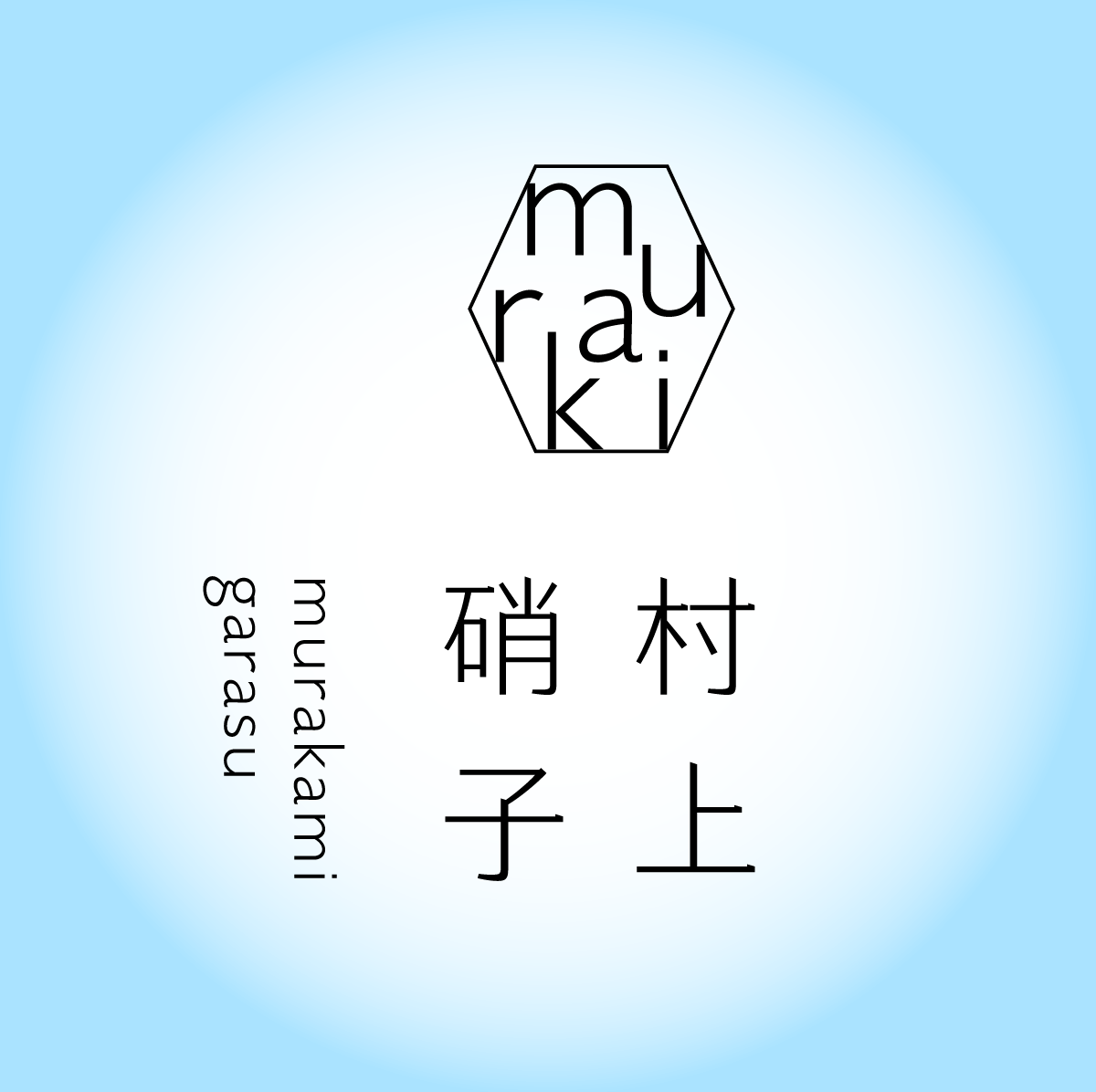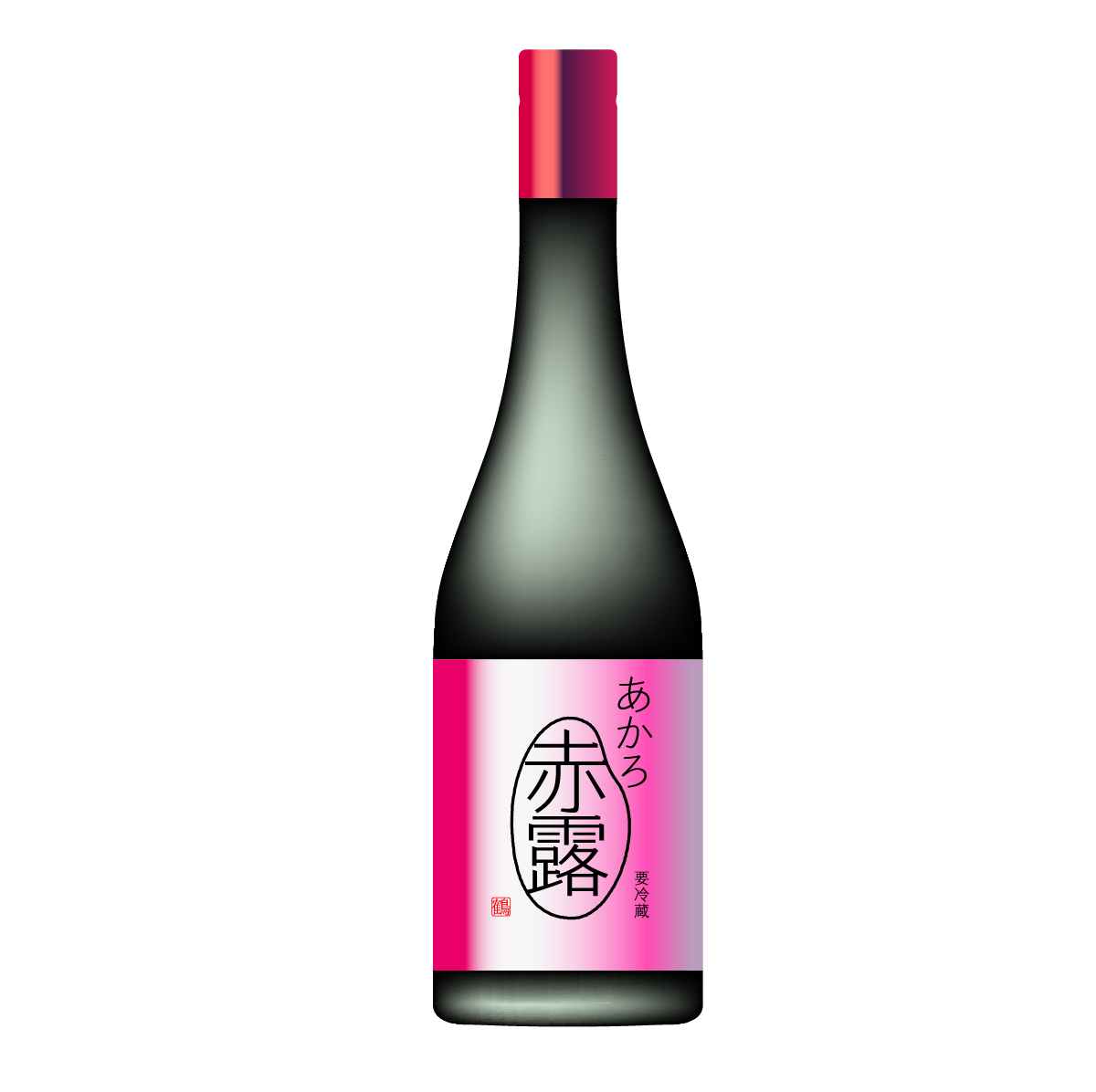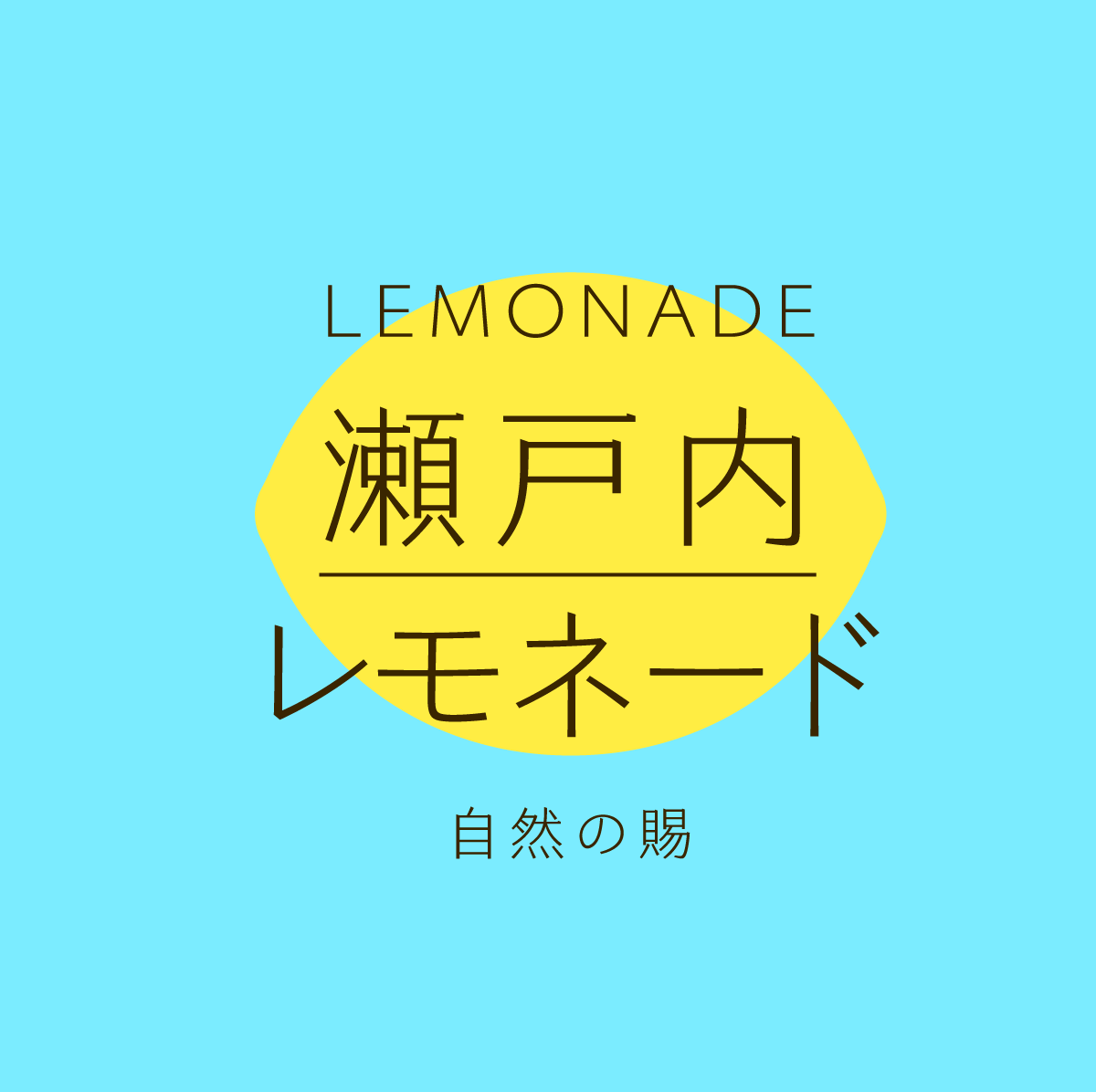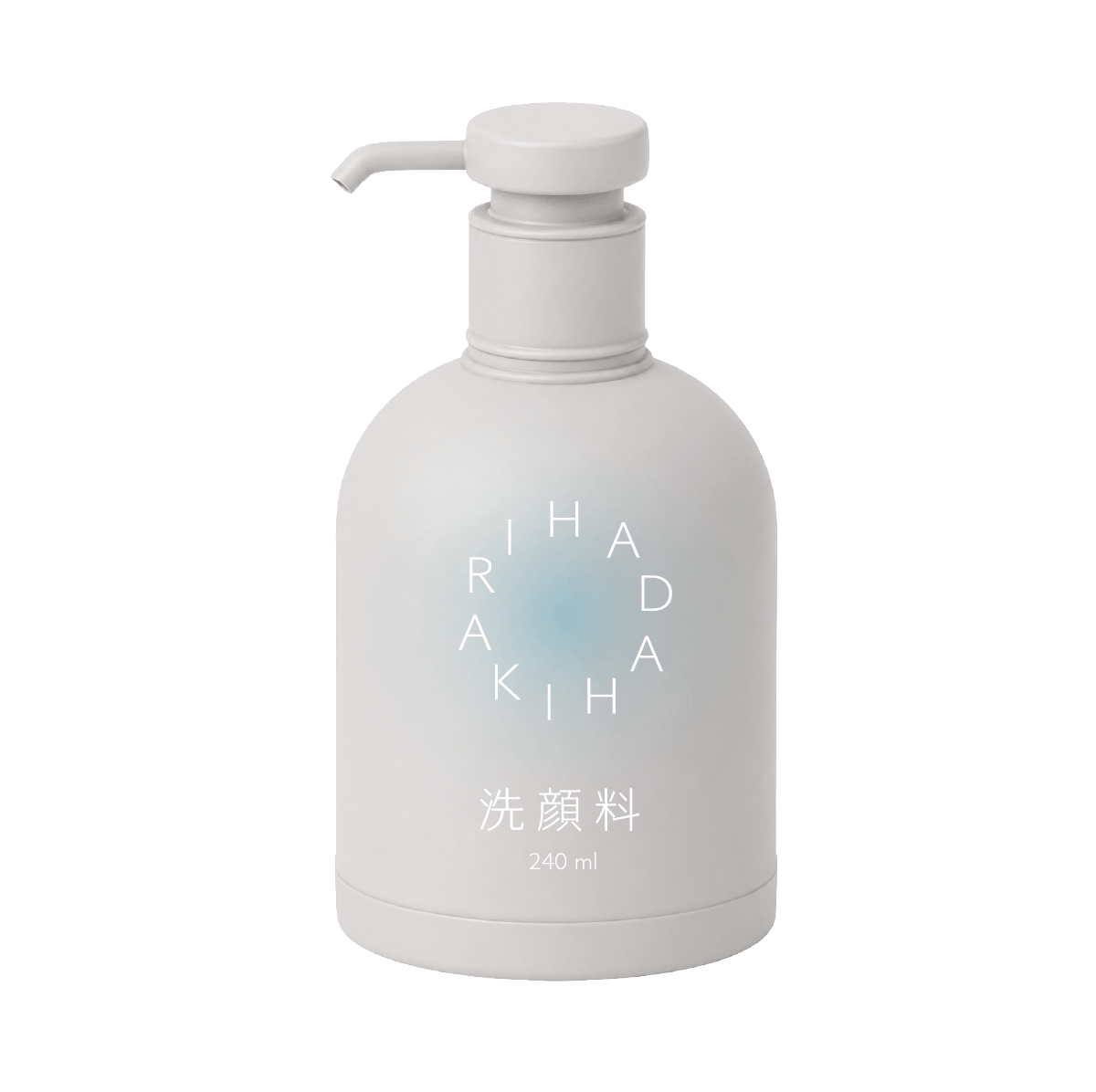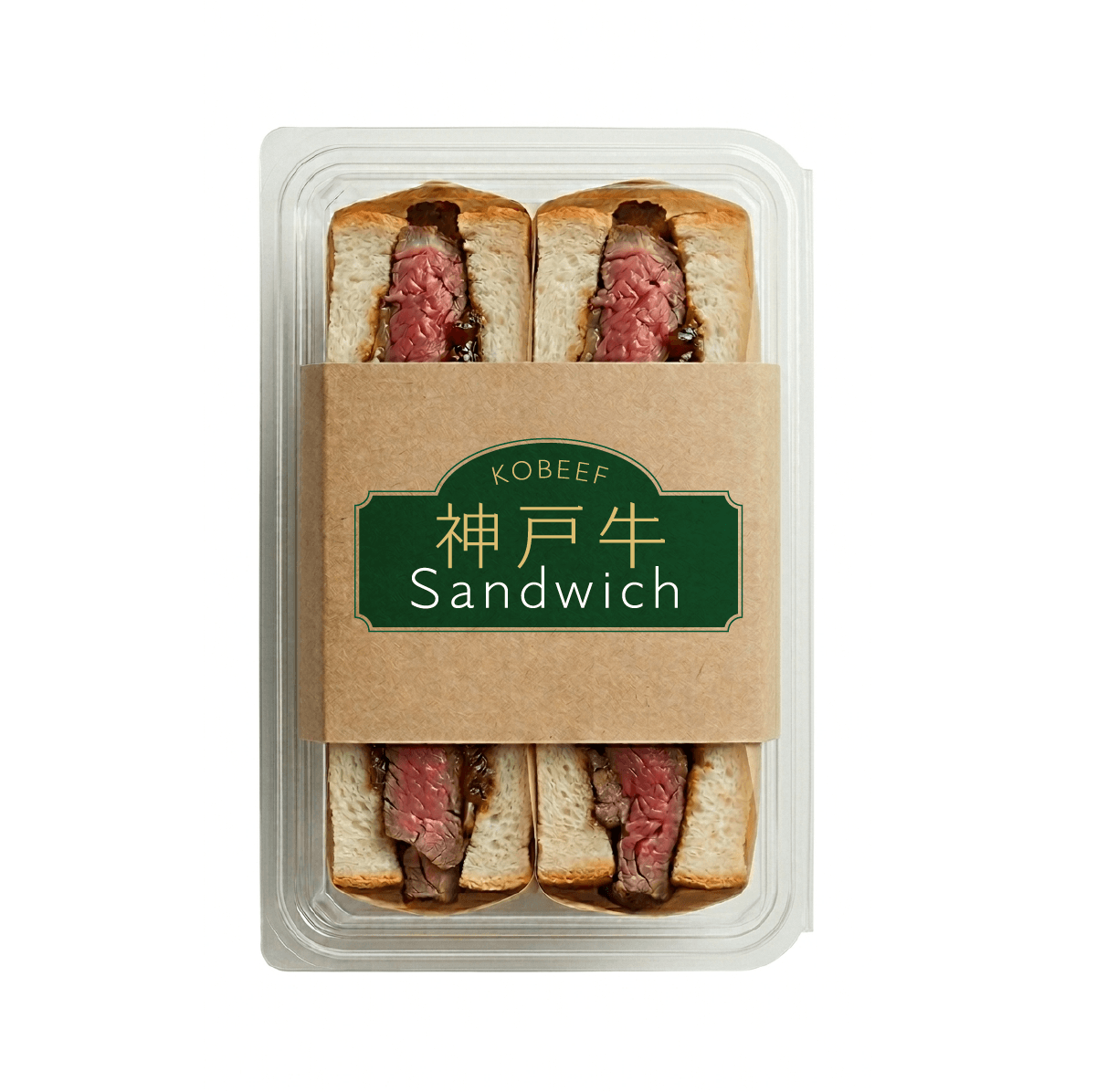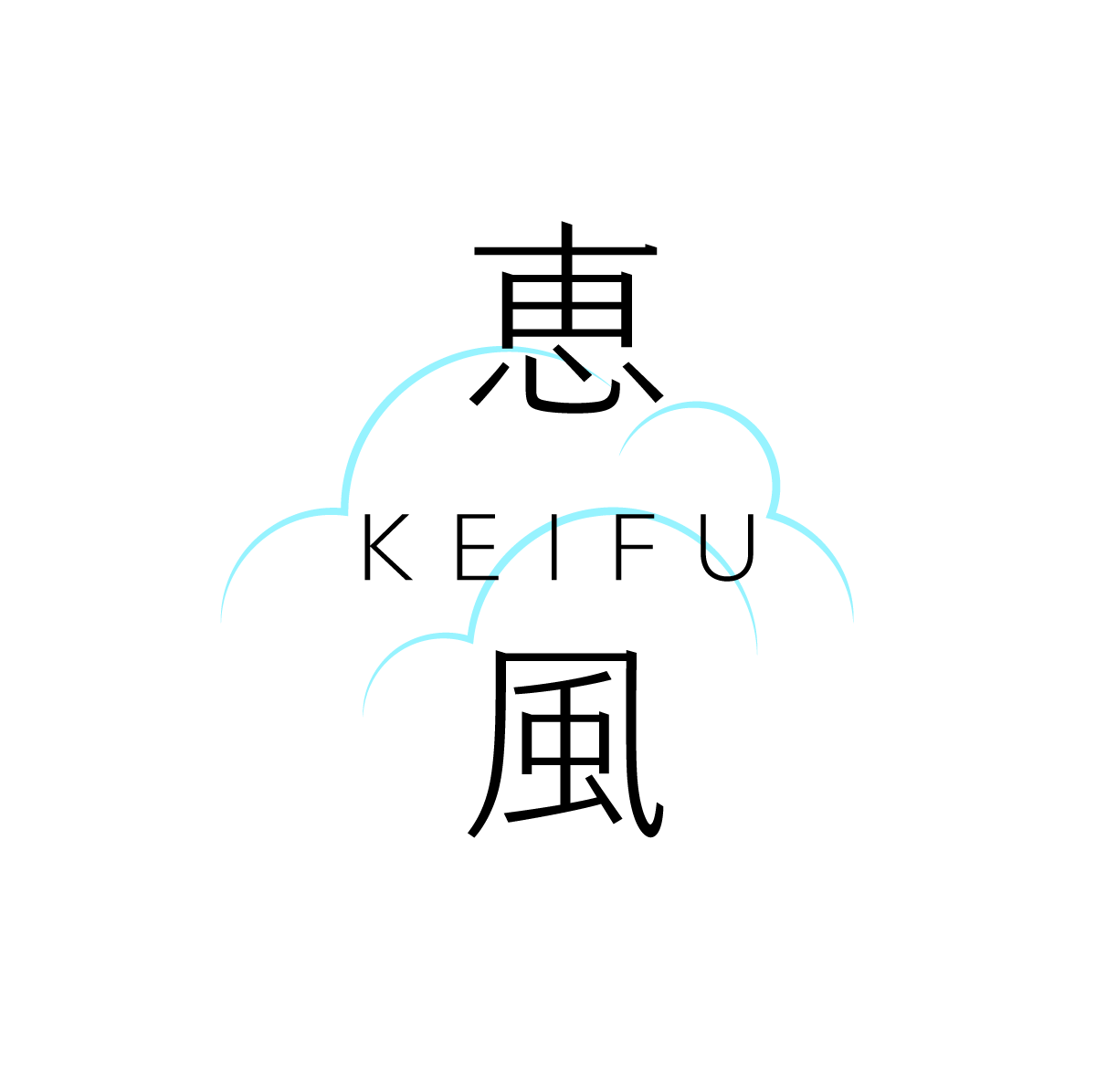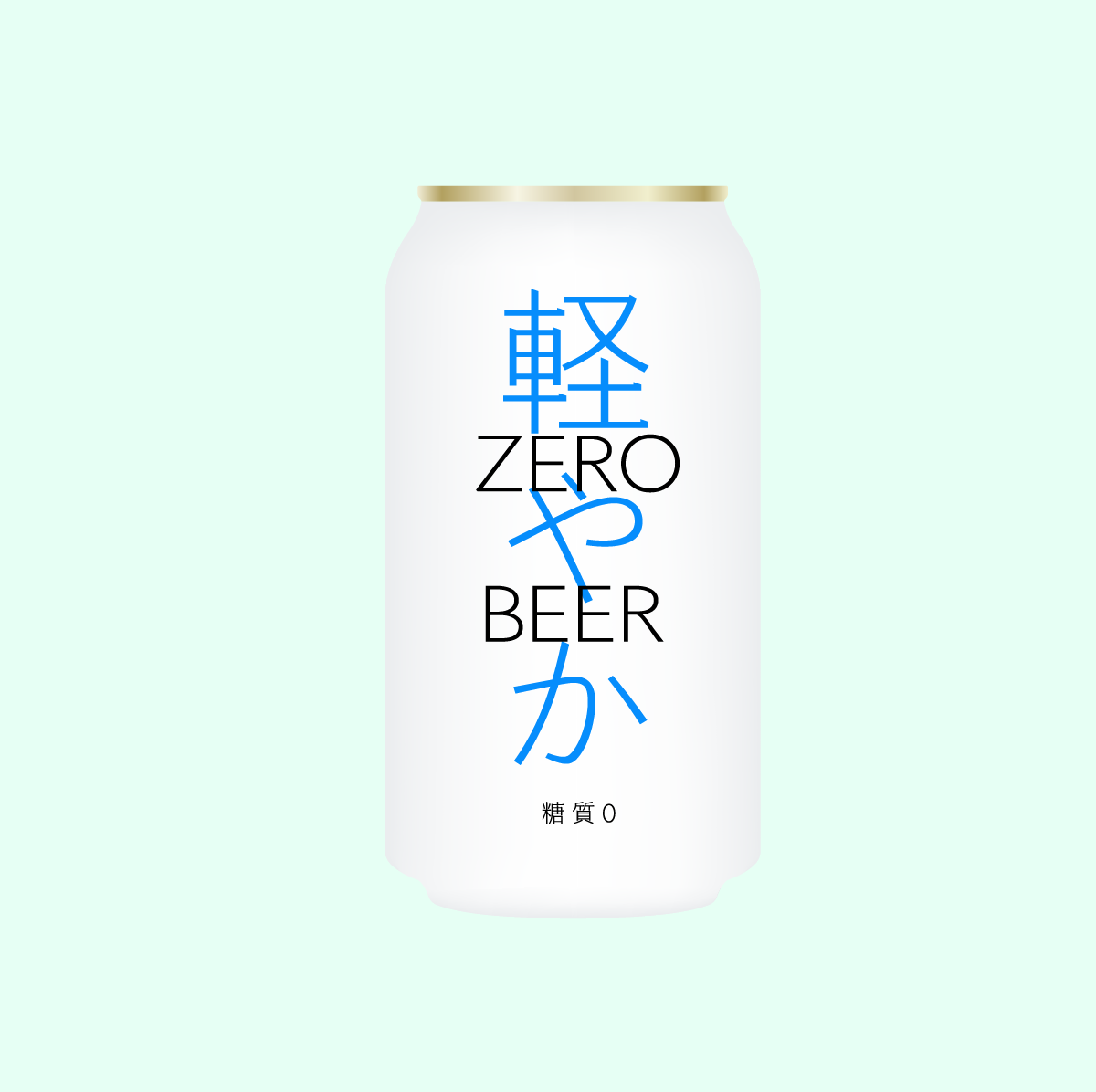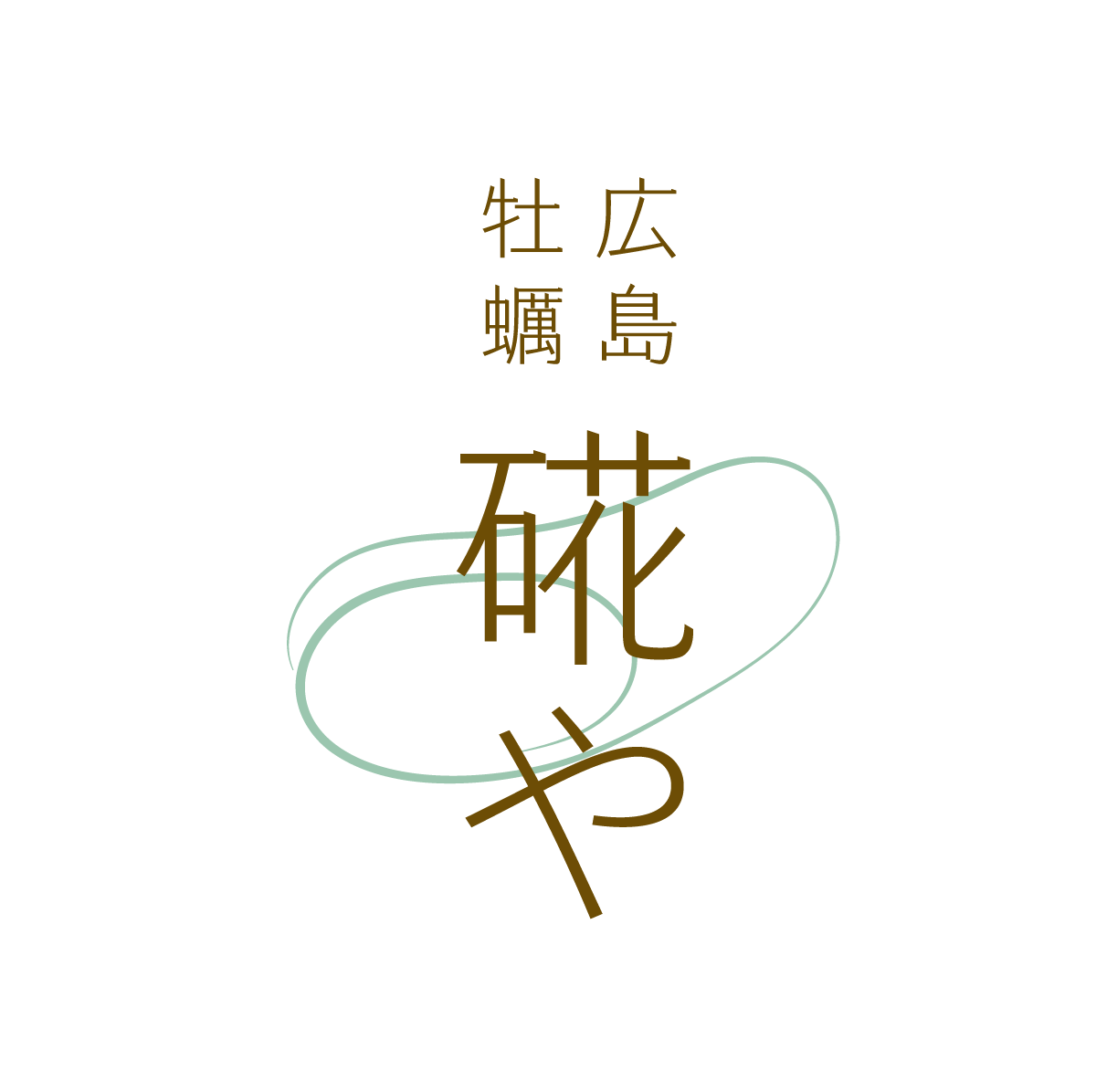
松韻 日本語版
1 種字重
松韻は、モダンでシンプル、そしてクリーンなスタイルを持つフォントです。松葉のように伸びやかで洗練されたデザインが、レイアウトに明るい透明感を生み出し、心地よい視覚体験を提供します。
- 施博瀚
- 日文
- 約 9,354 字
- Adobe Japan 1-3
字型設計師
施博瀚
擅長品牌企劃、識別設計、標準字設計。作品曾獲金點概念設計獎年度最佳設計、DFA亞洲最具影響力設計獎等,並相繼收錄於多本設計刊物中。現為 Bohan Graphi© 設計工作室負責人、中文字型「凝書體」創作者。著有《LOGO設計研究所》一書(如何出版)。